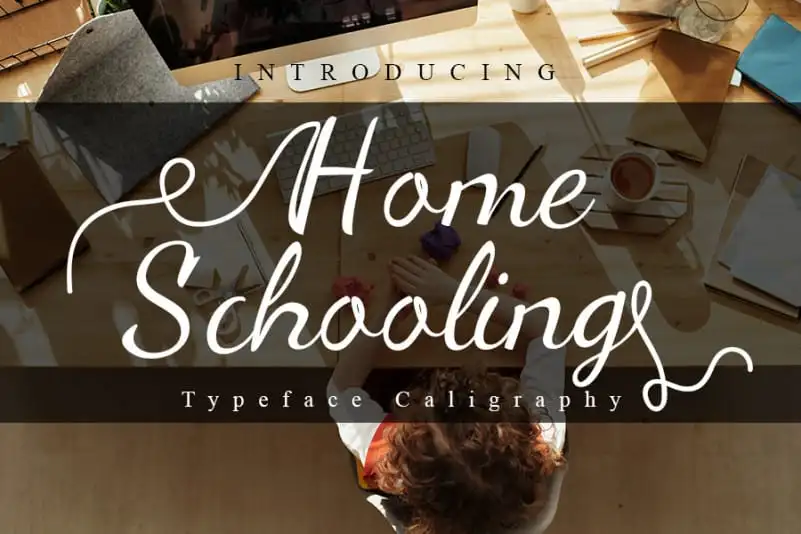
Home Schooling Calligraphy Font – Download Grátis
A Home Schooling Calligraphy Font é uma elegante tipografia que mantém seu sabor clássico do churrasco ao mesmo tempo moderno e renovador. Este design versátil atende a um amplo espectro de ideias criativas, desde selos e títulos até papel de carta personalizada. Com sua rica influência da tipografia, essa fonte é perfeita para aqueles que buscam expressar seu estilo pessoal em diversos projetos. Ela se destaca entre as demais por sua capacidade de trazer um toque autêntico e sofisticado a qualquer projeto, seja ele impresso ou digital. Ideal tanto para iniciantes quanto para os mais experientes, esta fonte é o complemento perfeito para aqueles que desejam incorporar uma pitada de elegância à sua rotina de aprendizado em casa ou ao seu próximo projeto visual.